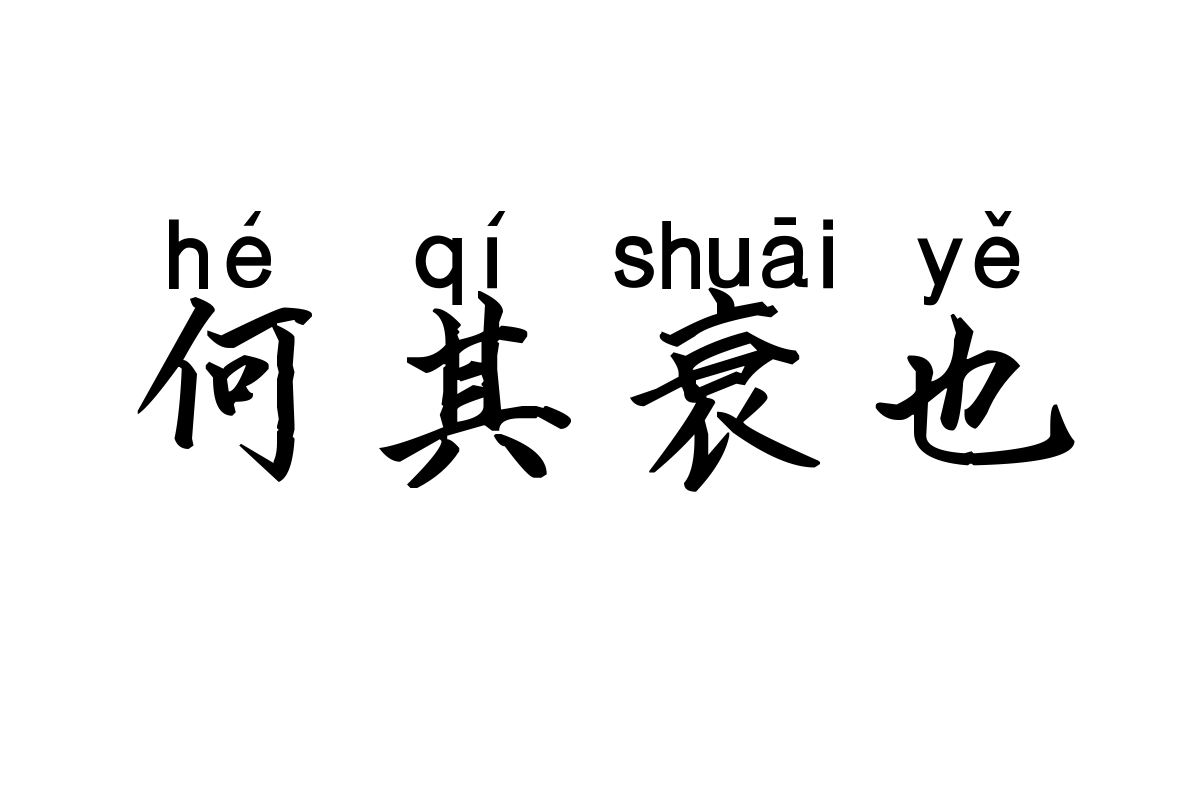
米开经典小楷拼音体是一种具有独特风格的字体,它结合了传统的书法艺术和现代的设计理念。这种字体的特点是笔画细腻、结构紧凑,给人一种优雅而庄重的感觉。
米开经典小楷拼音体的特点如下:
1. 笔画精细:这种字体的笔画非常细致,每一个笔画都经过精心设计,使得整个字体看起来既美观又具有艺术感。
2. 结构紧凑:与许多其他字体相比,米开经典小楷拼音体的结构更加紧凑,这使得它在视觉上更加集中,同时也使得字体在有限的空间内能够容纳更多的字符。
3. 优雅庄重:由于其独特的设计和笔画特点,米开经典小楷拼音体给人一种优雅而庄重的感觉,非常适合用于正式的文件或书籍中。
4. 易于阅读:虽然米开经典小楷拼音体看起来可能有些复杂,但它的笔画和结构都经过精心安排,使得整体的可读性非常好,适合快速阅读。
总的来说,米开经典小楷拼音体是一种独特而优雅的字体,它结合了传统书法艺术和现代设计理念,为人们提供了一种全新的视觉体验。
米开经典小楷拼音体